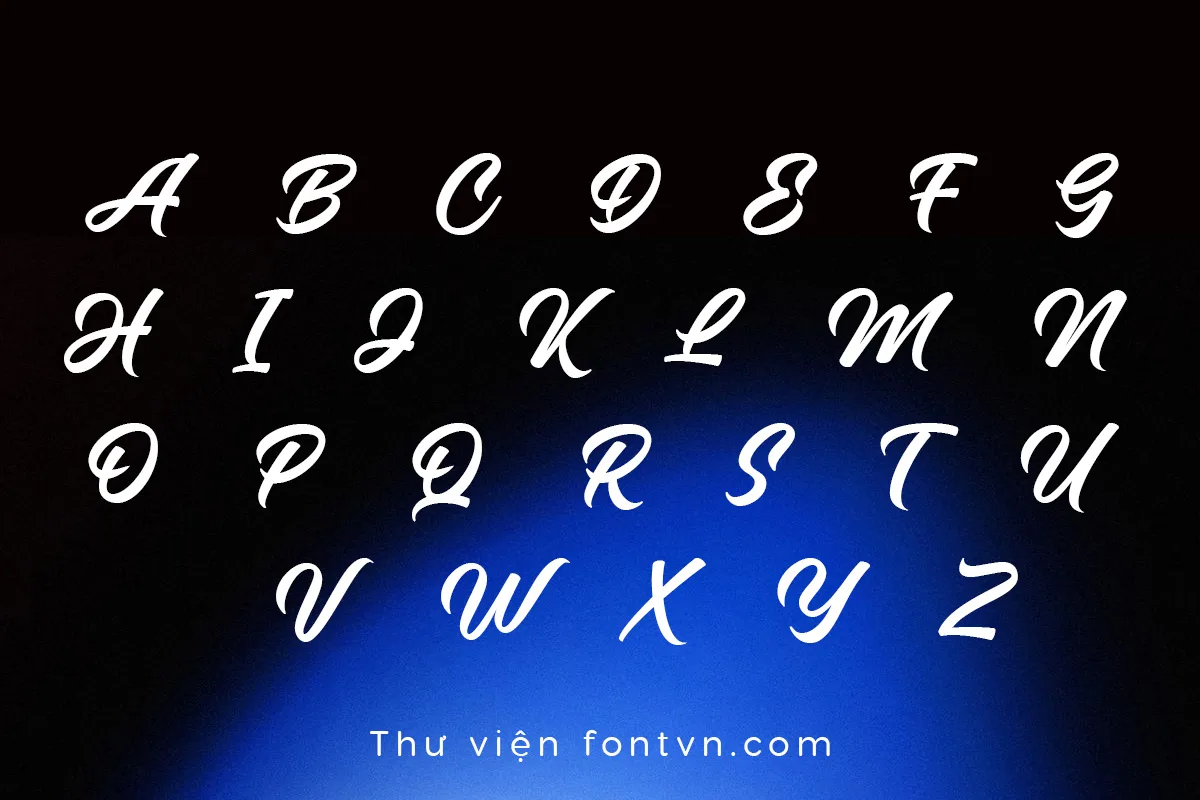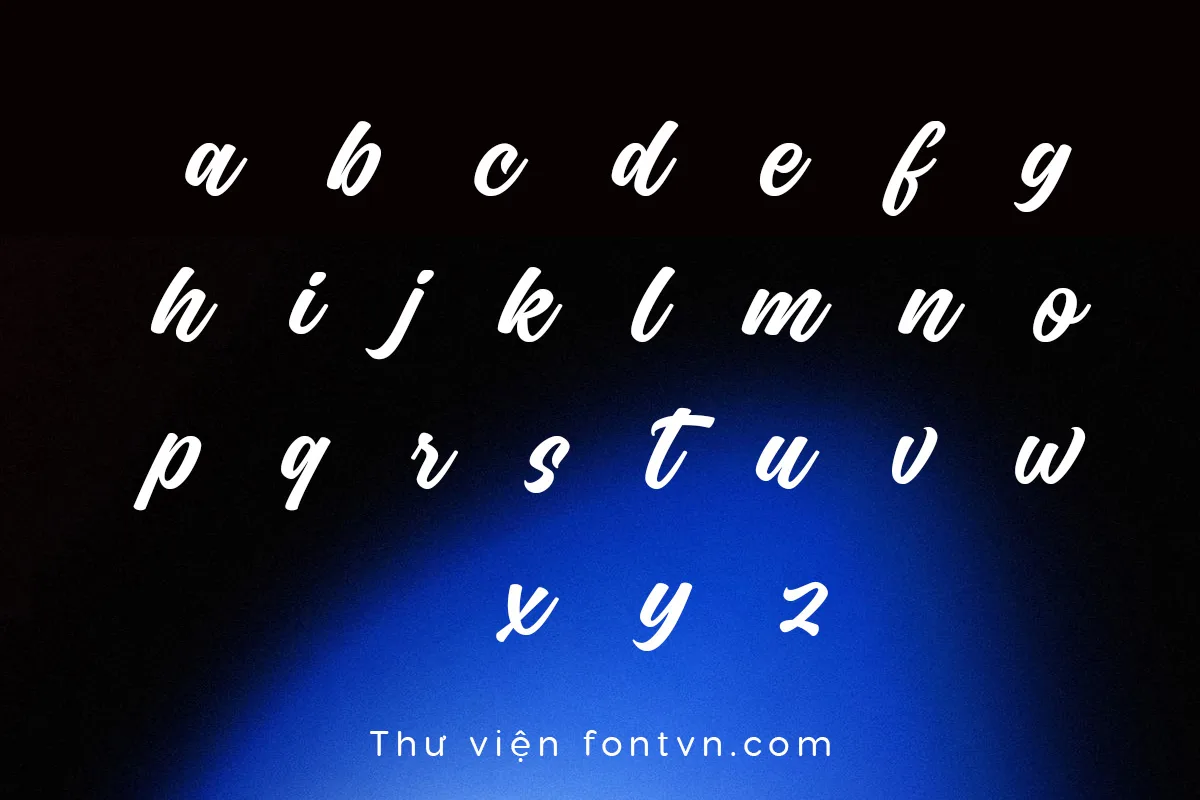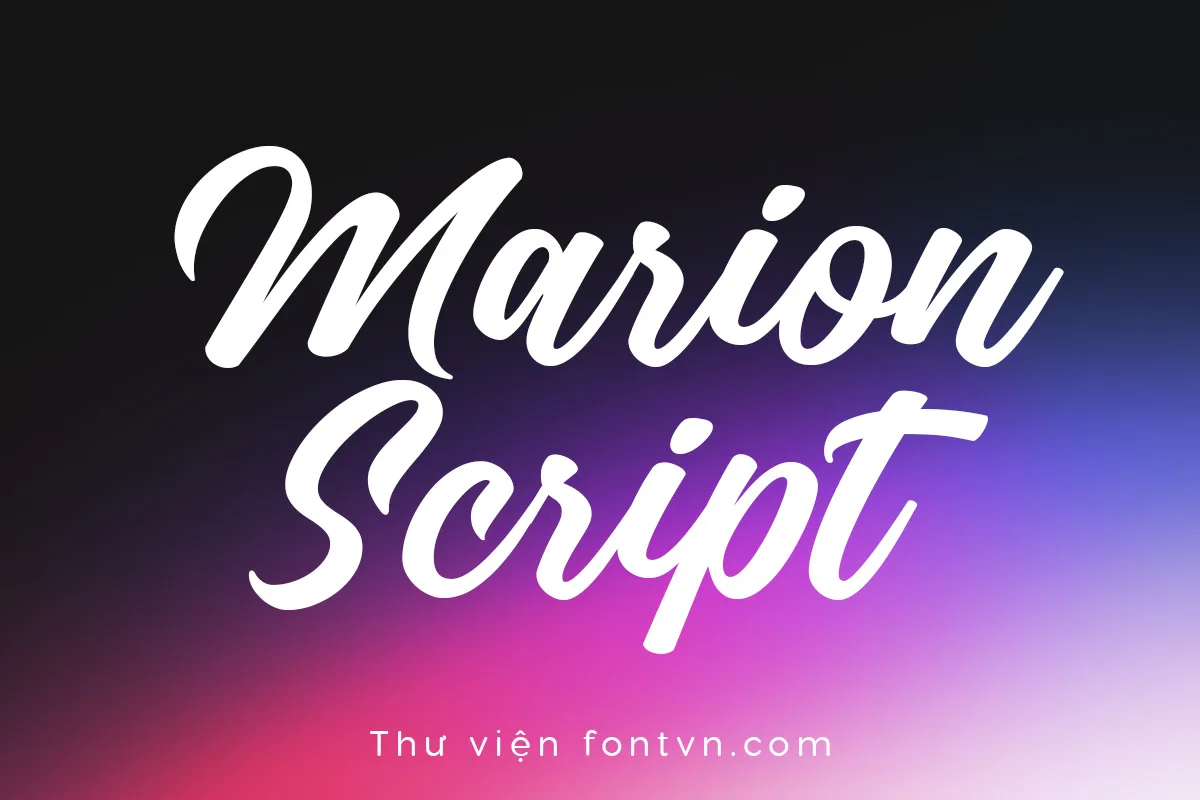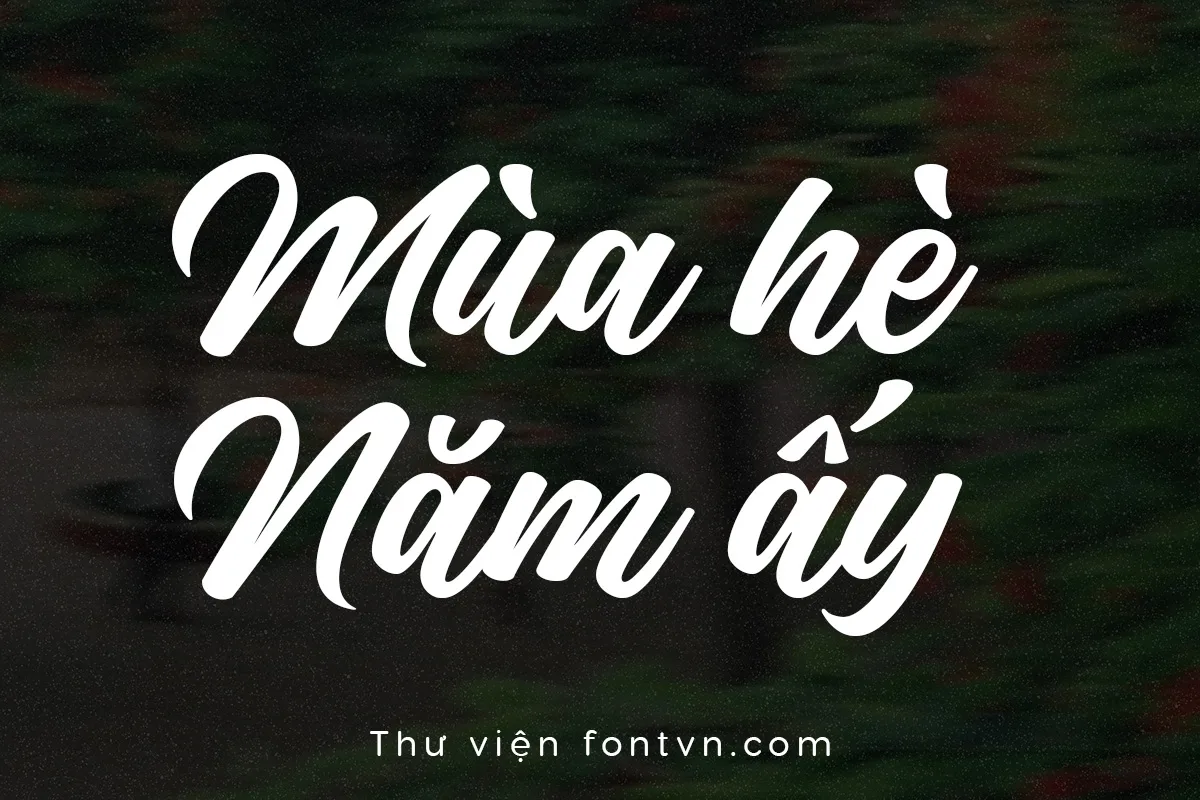
DVN Marion Script tiếng Việt – Font chữ lãng mạng và bay bổng
DVN Marion Script là một bộ font brush script mang đậm chất lãng mạn và bay bổng, nổi bật với độ tương phản cao giữa nét thanh tinh tế và nét đậm dứt khoát. Cấu trúc chữ được thiết kế với độ nghiêng tự nhiên, mô phỏng hoàn hảo lực nhấn của cọ mềm để tạo ra nhịp điệu uyển chuyển. Các ký tự có sự liên kết mượt mà kết hợp cùng đường chân chữ (baseline) hơi nảy, giúp tổng thể typography toát lên sự thanh lịch nhưng không hề cứng nhắc. Đặc biệt, trong phiên bản Việt hóa này, THDigi đã tinh chỉnh kỹ lưỡng hệ thống dấu câu tiếng Việt sao cho hòa quyện trọn vẹn vào các nét lượn đặc trưng, đảm bảo giữ nguyên tính thẩm mỹ nguyên bản của font chữ khi sử dụng với ngôn ngữ bản địa.
Nhờ đặc tính thị giác sang trọng và đầy cảm xúc, bộ font này là giải pháp hoàn hảo cho các dự án thiết kế cần sự tinh tế và cá nhân hóa. DVN Marion Script phát huy tối đa sức hút khi được ứng dụng làm điểm nhấn cho thiệp cưới, thiệp mời sự kiện (Save The Date), hoặc tiêu đề album ảnh kỷ niệm. Bên cạnh đó, nét chữ mềm mại và nghệ thuật này cũng đặc biệt phù hợp để thiết kế logo, xây dựng bộ nhận diện thương hiệu cho các ngành hàng làm đẹp, thời trang, mỹ phẩm, cũng như thiết kế bao bì sản phẩm cao cấp và quote truyền cảm hứng.